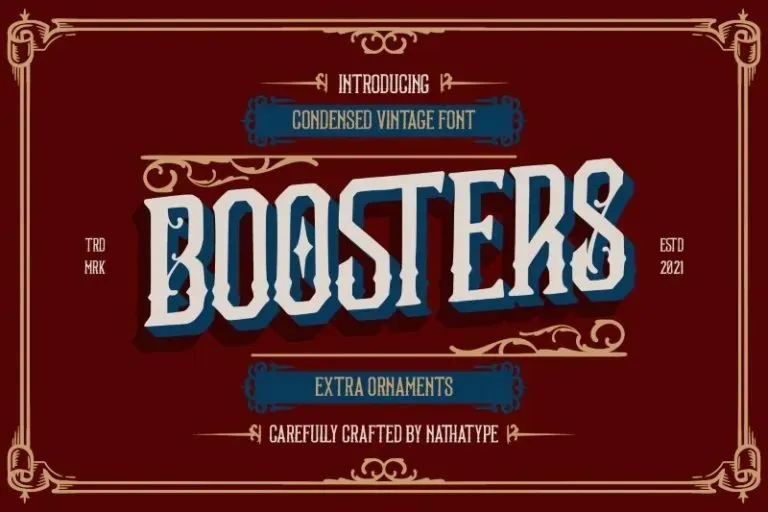
Boosters Font – Fonte Grátis
Boosters Font
A Boosters Font é uma nova adição à família de fontes Display do 99designs. Esta elegante tipografia vintage em estilo Blackletter leva o seu design ao próximo nível, combinando características clássicas dos anos Victorios com um toque moderno que a torna perfeitamente adaptável para diversos contextos e projetos. Ideal tanto para estilos tradicionais quanto contemporâneos, essa fonte vintage é uma ótima escolha para qualquer projeto, seja ele de branding ou promoção. Suas formas arredondadas e texturas vintage criam um visual atraente que combina perfeitamente com o estilo retro, oferecendo uma grande versatilidade em aplicação para logotipos, capas de livros, panfletos, camisetas, identidades visuais e anúncios. Com uma fonte como essa à sua disposição, suas criações se tornam ainda mais atraentes e memoráveis.